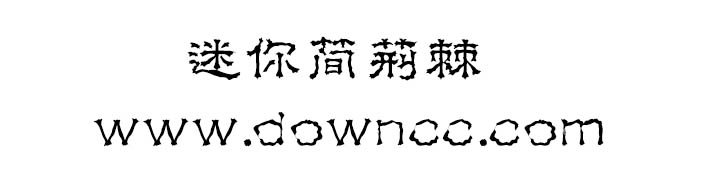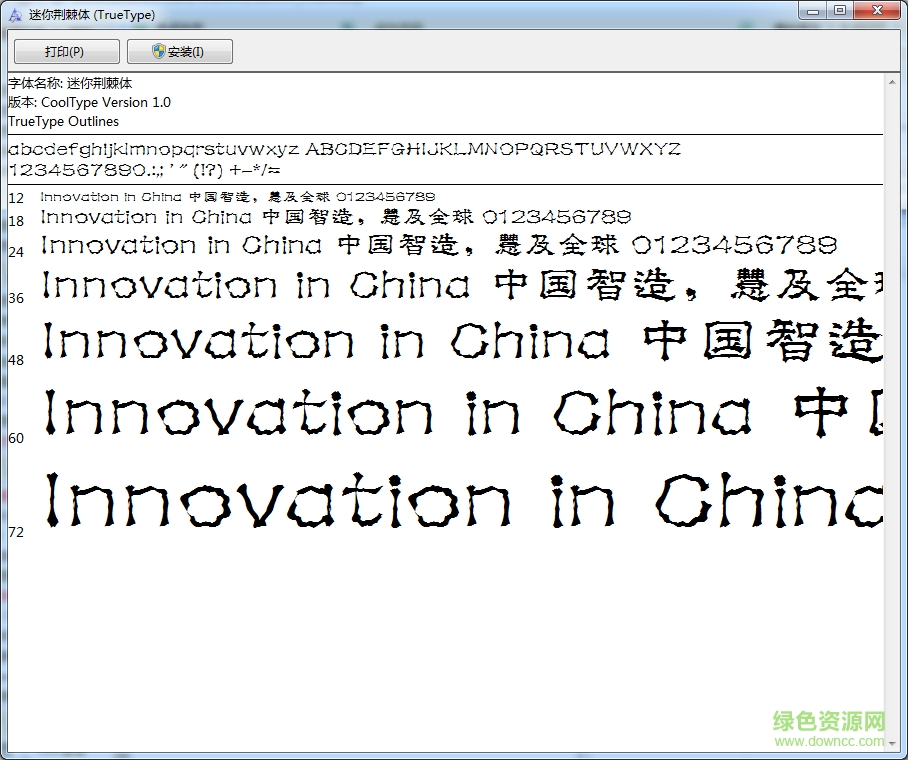
迷你簡(jiǎn)荊棘體是一款非常有個(gè)性電腦字體軟件,字體風(fēng)格迥異彰顯個(gè)性,常用于美工設(shè)計(jì)之中,一鍵安裝即可使用。快來(lái)綠色資源網(wǎng)下載體驗(yàn)吧!
今天小編為你帶來(lái)迷你簡(jiǎn)荊棘字體。這個(gè)字體的結(jié)構(gòu)如同荊棘圍繞在一起,看著還蠻有美感的,很適合廣告設(shè)計(jì)、平面設(shè)計(jì)、印刷包裝、正文標(biāo)題等人員使用。